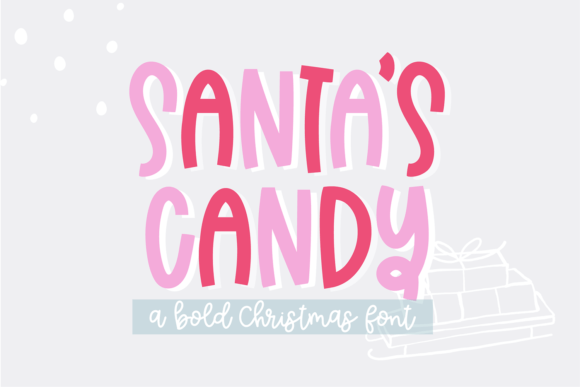
Santa's Candy
適切なデザイン要素を見つけるのは難しい場合がありますが、Santa's Candyは作品を即座に引き立てる優れたコレクションを提供します。
POD(オンデマンド印刷)製品、結婚式の招待状、またはソーシャルメディアのグラフィックを作成している場合でも、Santa's Candyは理想的です。